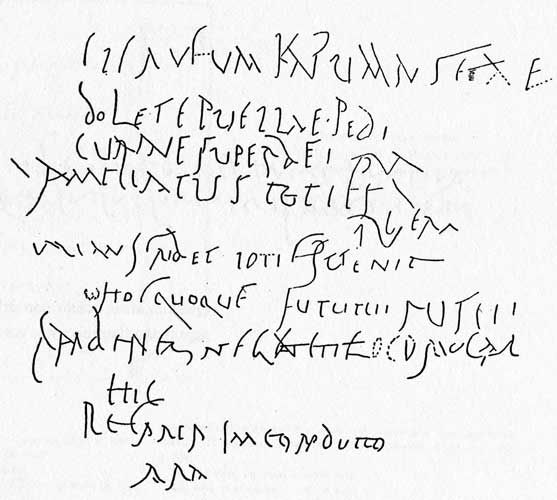
Archaische Handschrift mit pompejianischem Touch
Diese wunderschöne Handschrift ist auf meinem Schreibtisch gelandet. Und wiedermal bin ich ratlos, wie sie wohl heißen mag. Thanx.
"wunderschön" ist. Da stimmt doch gar nichts dran: unausgeglichene Wortbilder, schwerlesbare und missverständlich Buchstaben, keine gescheite Zurichtung und entsprechend ungleichmäßiger Grauwert ... also ich weiß wirklich nicht ...
vielleicht kann man mir das mal erklären?
Was ich auch gern wüßte: was ist ein "pompejanischer Touch"?
also ich weiß wirklich nicht ...
Ich auch nicht, daher:
Was ich auch gern wüßte: was ist ein "pompejanischer Touch"?
= dem Untergang geweiht? ;-)
Was ich auch gern wüßte: was ist ein "pompejanischer Touch"?
Entfernt an pompeianische Graffiti erinnerende Linienführung?
Lieber gutenberger,
hier mal was aus der Schriftgeschichte: pompejianische Graffiti. Da hast du ganz recht, sieht echt schlimm aus. Aber weißt du was? Ich mag es trotzdem! :rockon: